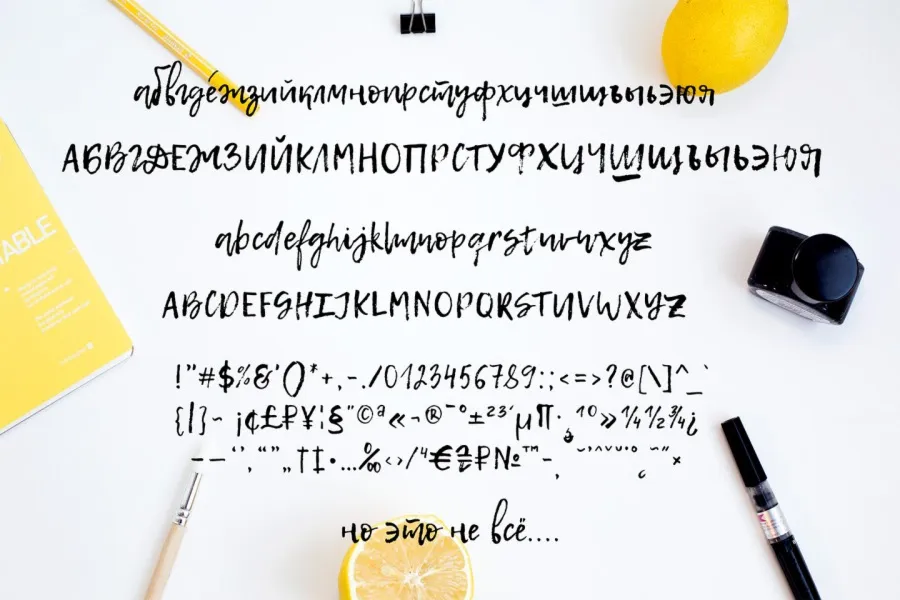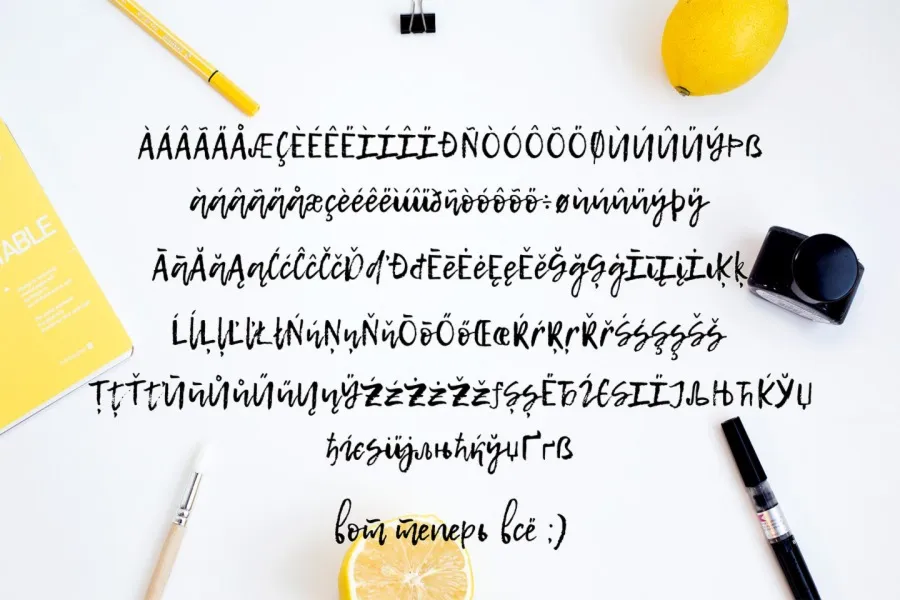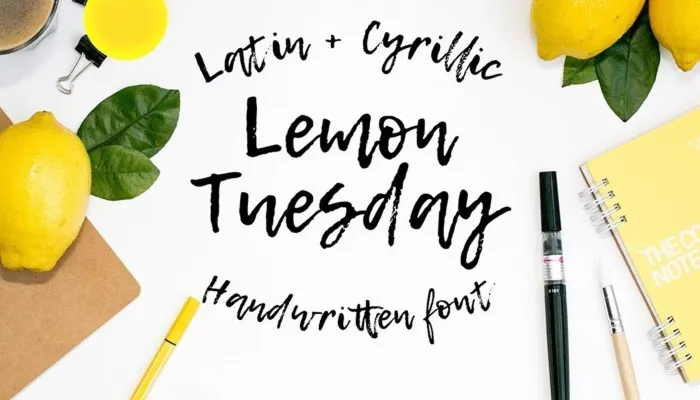
Шрифт LEMON TUESDAY
Представляем вашему вниманию сверхакцидентный шрифт.
Lemon Tuesday ориентирован в первую очередь на короткие эмоциональные надписи, преимущественно для создания красивого контента в социальных сетях и нишевых медиа. Шрифт содержит базовый набор кириллических знаков, а также расширенную кассу знаков для латиницы.